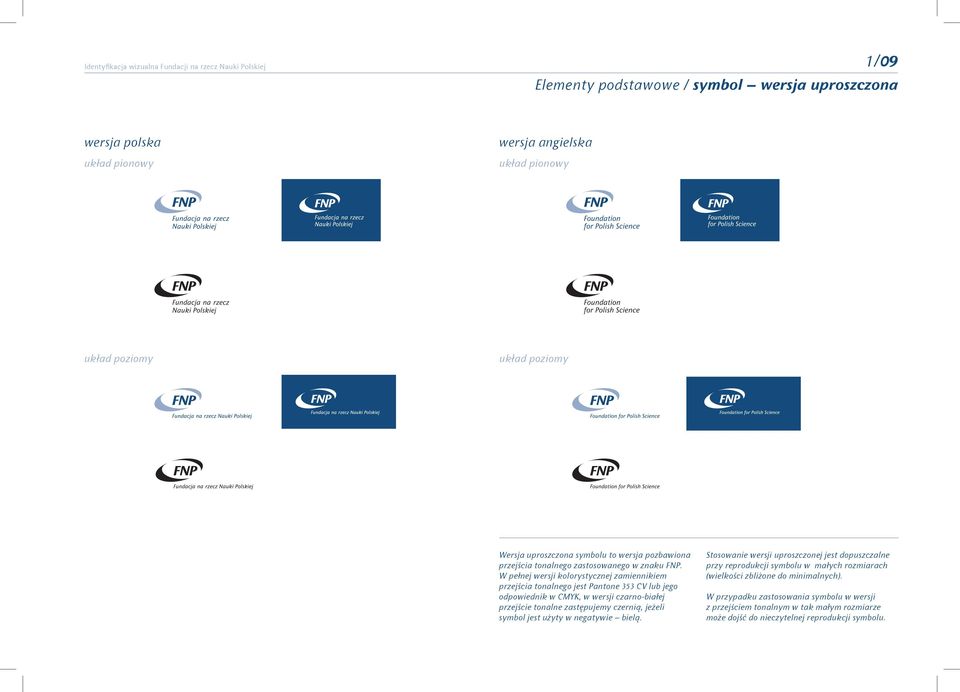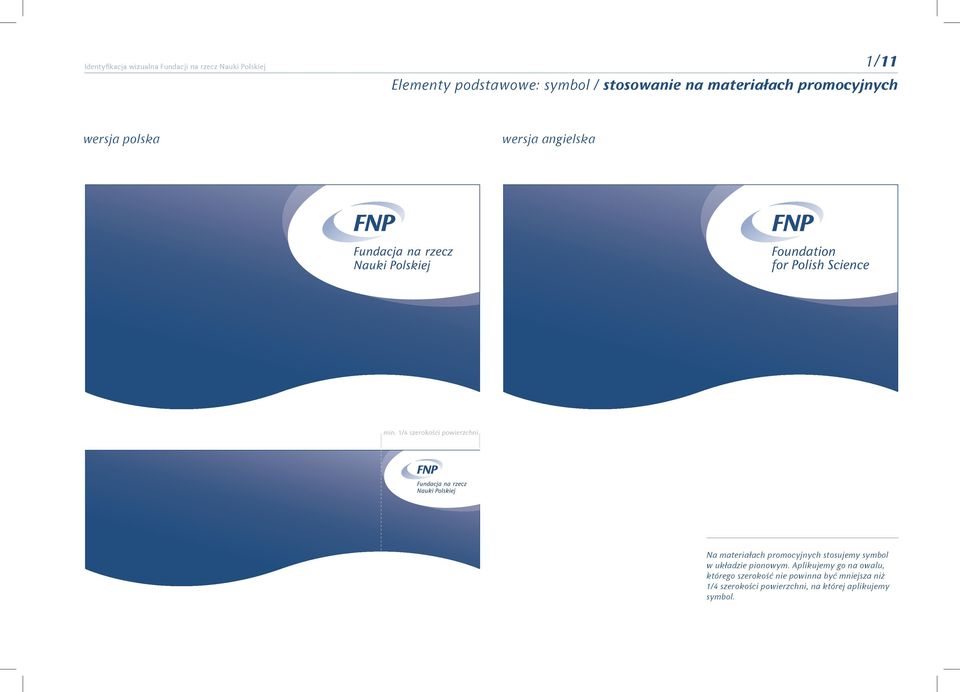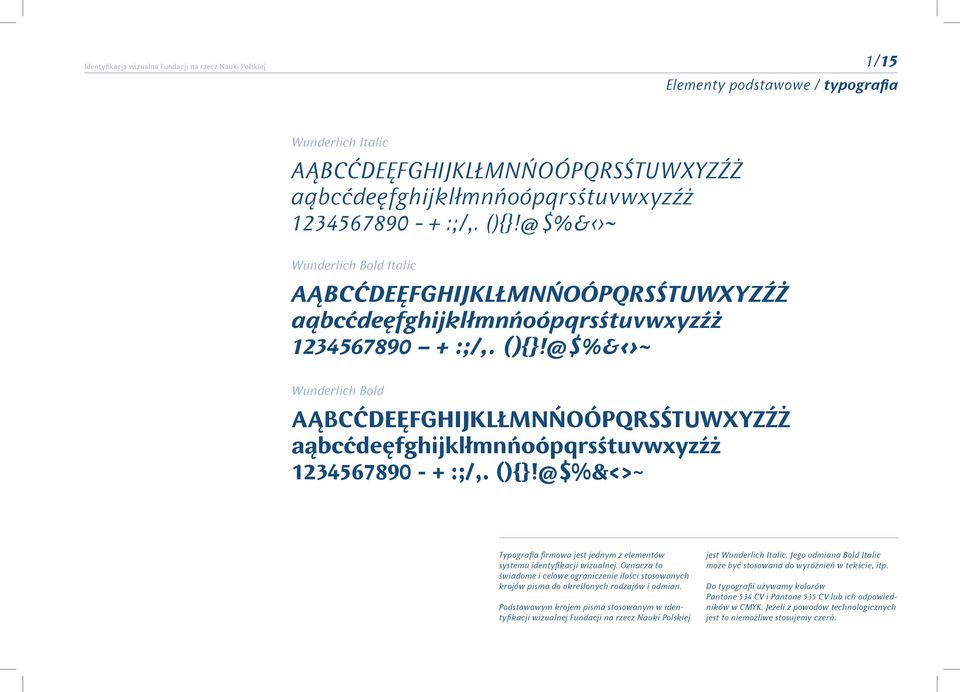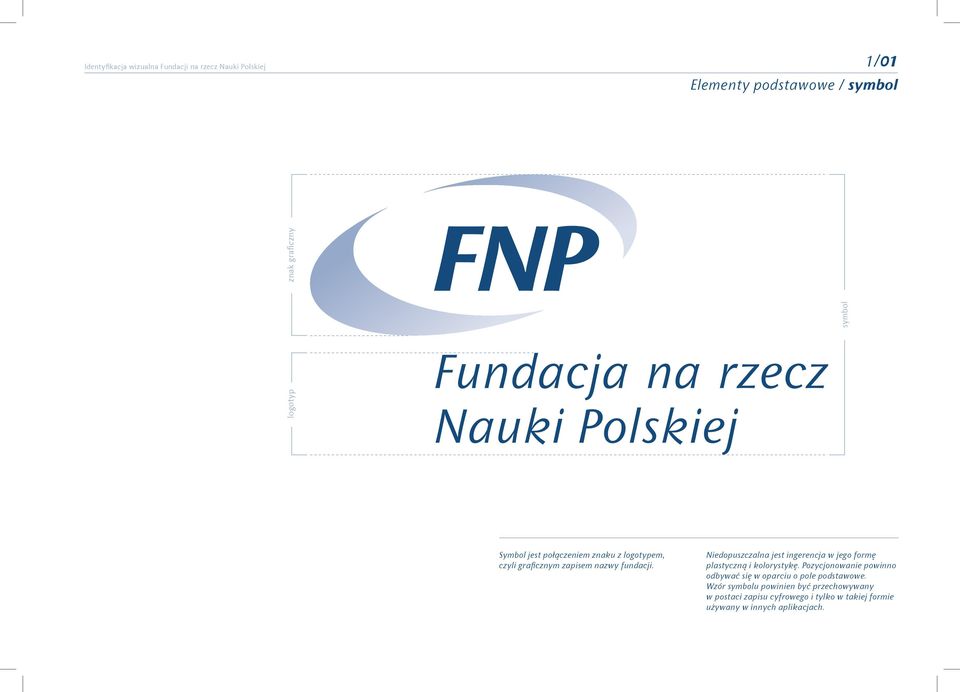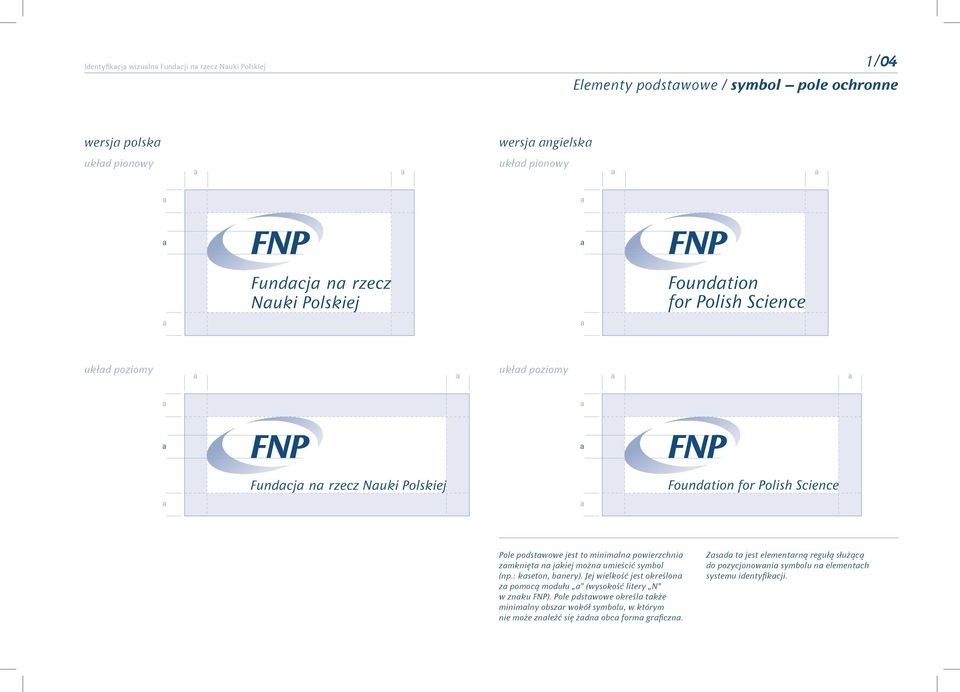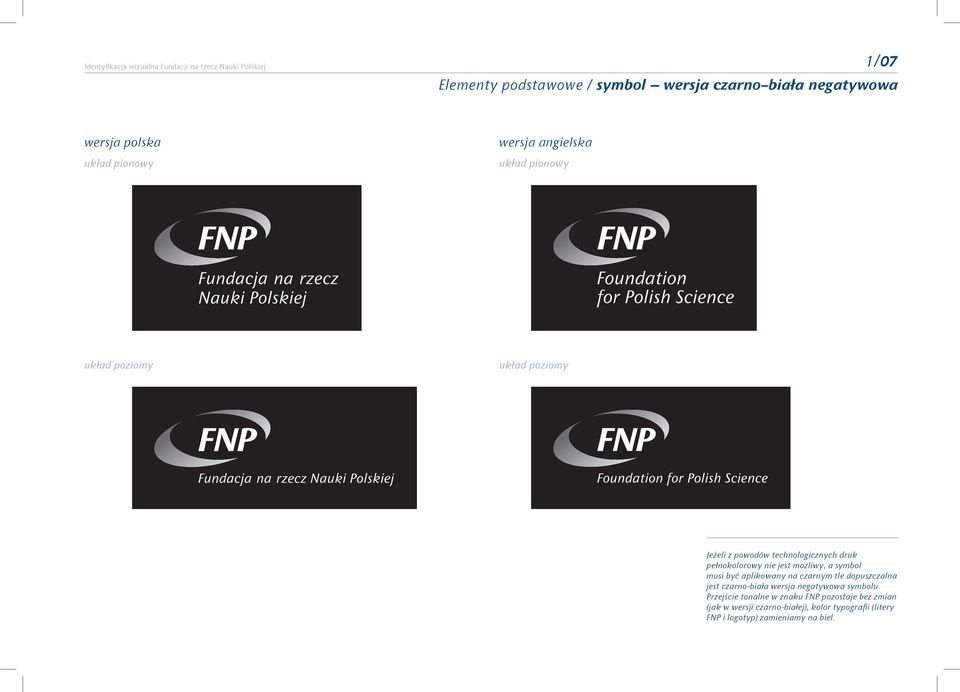
symbol dodatkowy element graficzny kolorystyka typografia
1 Identyfikcj wizuln Fundcji n rzecz Nuki Polskiej 1/00 Elementy podstwowe symbol dodtkowy element grficzny kolorystyk typogrfi
2 Identyfikcj wizuln Fundcji n rzecz Nuki Polskiej 1/01 Elementy podstwowe / symbol logotyp symbol znk grficzny Symbol jest połączeniem znku z logotypem, czyli grficznym zpisem nzwy fundcji. Niedopuszczln jest ingerencj w jego formę plstyczną i kolorystykę. Pozycjonownie powinno odbywć się w oprciu o pole podstwowe. Wzór symbolu powinien być przechowywny w postci zpisu cyfrowego i tylko w tkiej formie używny w innych plikcjch.
3 Identyfikcj wizuln Fundcji n rzecz Nuki Polskiej 1/02 Elementy podstwowe: symbol / znk grficzny w wersji relifowej (tłoczenie wklęsłe lub wypukłe, grwerownie) W systemie identyfikcji wizulnej FNP znk grficzny może być stosowny bez logotypu. Jest to dopuszczlne przy technologii tłoczeni lub grwerowni znku w różnego rodzju mteriłch (ppier, metl).
4 Identyfikcj wizuln Fundcji n rzecz Nuki Polskiej 1/03 Elementy podstwowe / symbol wersje wersj polsk ukłd pionowy wersj ngielsk ukłd pionowy ukłd poziomy Symbol FNP występuje w dwóch wersjch językowych: polskiej i ngielskiej, dodtkowo kżd z wersji językowych w dwóch ukłdch kompozycyjnych: pionowym i poziomym. W mirę możliwości nleży stosowć ukłd pionowy symbolu. Ukłd poziomy służy do stosowni n długich i wąskich poziomych powierzchnich (np. bnner).
5 Identyfikcj wizuln Fundcji n rzecz Nuki Polskiej 1/04 Elementy podstwowe / symbol pole ochronne wersj polsk wersj ngielsk ukłd pionowy ukłd poziomy Pole podstwowe jest to minimln powierzchni zmknięt n jkiej możn umieścić symbol (np.: kseton, bnery). Jej wielkość jest określon z pomocą modułu (wysokość litery N w znku FNP). Pole pdstwowe określ tkże minimlny obszr wokół symbolu, w którym nie może znleźć się żdn obc form grficzn. Zsd t jest elementrną regułą służącą do pozycjonowni symbolu n elementch systemu identyfikcji.
6 Identyfikcj wizuln Fundcji n rzecz Nuki Polskiej 1/05 Elementy podstwowe / symbol wersj negtywow wersj polsk ukłd pionowy wersj ngielsk ukłd pionowy ukłd poziomy W sytucji jeżeli symbol musi być plikowny n ciemnym tle dopuszczln jest wersj negtywow symbolu. Przejście tonlne w znku FNP pozostje bez zmin, kolor typogrfii (litery FNP i logotyp) zmienimy n biel. Znk w tej wersji stosujemy tylko w wyjątkowych sytucjch. Nleży pmiętć o konieczności utrzymni mksymlnego kontrstu pomiędzy kolorem symbolu, kolorem tł.
7 Identyfikcj wizuln Fundcji n rzecz Nuki Polskiej 1/06 Elementy podstwowe / symbol wersj czrno-bił wersj polsk ukłd pionowy wersj ngielsk ukłd pionowy ukłd poziomy Wersj czrno-bił powinn być stosown w wyjątkowych sytcjch, np. jeżeli z powodów technologicznych druk pełnokolorowy nie jest możliwy.
8 Identyfikcj wizuln Fundcji n rzecz Nuki Polskiej 1/07 Elementy podstwowe / symbol wersj czrno-bił negtywow wersj polsk ukłd pionowy wersj ngielsk ukłd pionowy ukłd poziomy Jeżeli z powodów technologicznych druk pełnokolorowy nie jest możliwy, symbol musi być plikowny n czrnym tle dopuszczln jest czrno-bił wersj negtywow symbolu. Przejście tonlne w znku FNP pozostje bez zmin (jk w wersji czrno-biłej), kolor typogrfii (litery FNP i logotyp) zmienimy n biel.
9 Identyfikcj wizuln Fundcji n rzecz Nuki Polskiej 1/08 Elementy podstwowe / symbol wielkości minimlne wersj polsk wersj ngielsk ukłd pionowy 12 mm 12 mm 12 mm 12 mm ukłd poziomy 12 mm 12 mm 12 mm 12 mm Przy zbyt dużych zmniejszenich znk stje się znieksztłcony, typogrfi w logotypie przestje być czyteln. Aby tego uniknąć, określono minimlną wysokość symbolu.
10 Identyfikcj wizuln Fundcji n rzecz Nuki Polskiej 1/09 Elementy podstwowe / symbol wersj uproszczon wersj polsk ukłd pionowy wersj ngielsk ukłd pionowy ukłd poziomy Wersj uproszczon symbolu to wersj pozbwion przejści tonlnego zstosownego w znku FNP. W pełnej wersji kolorystycznej zmiennikiem przejści tonlnego jest Pntone 353 CV lub jego odpowiednik w CMYK, w wersji czrno-biłej przejście tonlne zstępujemy czernią, jeżeli symbol jest użyty w negtywie bielą. Stosownie wersji uproszczonej jest dopuszczlne przy reprodukcji symbolu w młych rozmirch (wielkości zbliżone do minimlnych). W przypdku zstosowni symbolu w wersji z przejściem tonlnym w tk młym rozmirze może dojść do nieczytelnej reprodukcji symbolu.
11 Identyfikcj wizuln Fundcji n rzecz Nuki Polskiej 1/10 Elementy podstwowe / symbol pozycjonownie wersj polsk wersj ngielsk ukłd pionowy ukłd poziomy Odległości od krwędzi dobier się indywidulnie w zleżności od wielkości płszczyzny i wielkości symbolu, le zwsze nleży pmiętć o minimlnej odległości od krwędzi wyznczonej przez pole podstwowe symbolu (moduł ). Symbol w ukłdzie poziomym powinno stosowć się n długich i wąskich powierzchnich poziomych. moduł = wysokość litery N w znku FNP
12 Identyfikcj wizuln Fundcji n rzecz Nuki Polskiej 1/11 Elementy podstwowe: symbol / stosownie n mteriłch promocyjnych wersj polsk wersj ngielsk min. 1/4 szerokości powierzchni N mteriłch promocyjnych stosujemy symbol w ukłdzie pionowym. Aplikujemy go n owlu, którego szerokość nie powinn być mniejsz niż 1/4 szerokości powierzchni, n której plikujemy symbol.